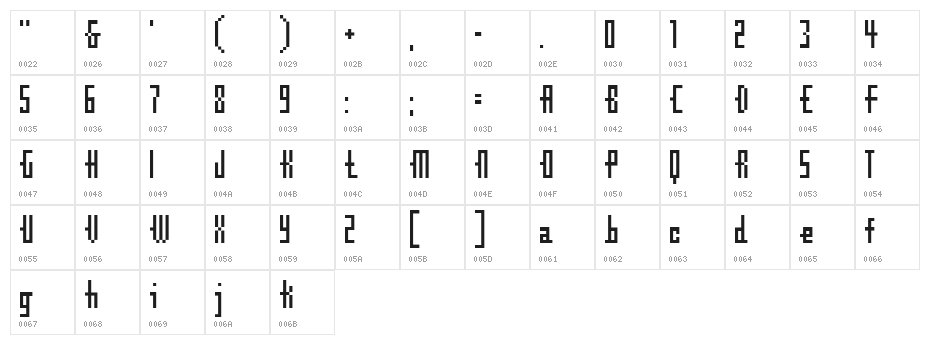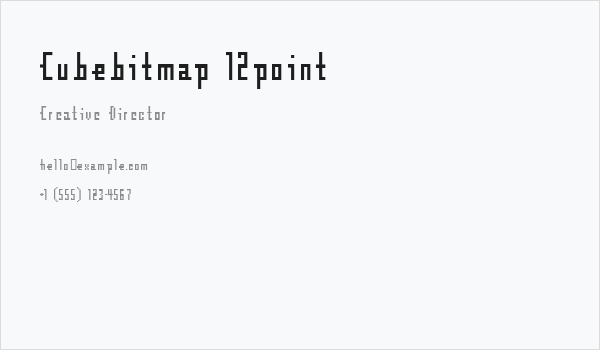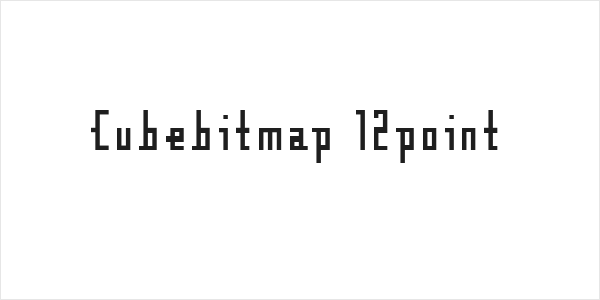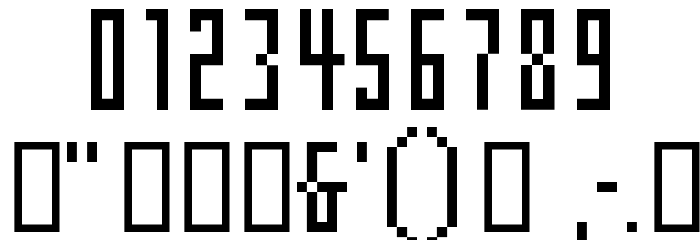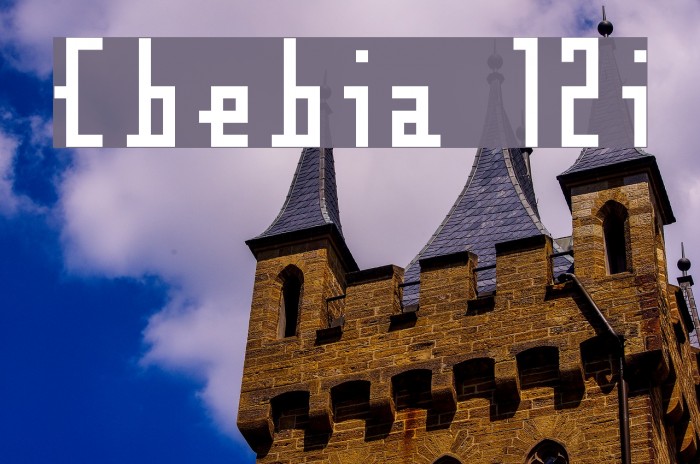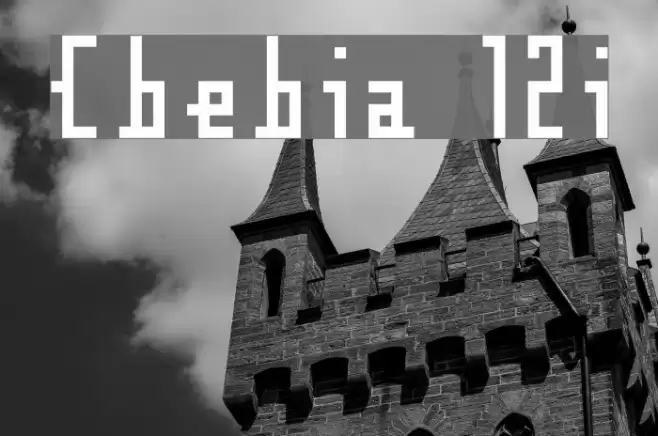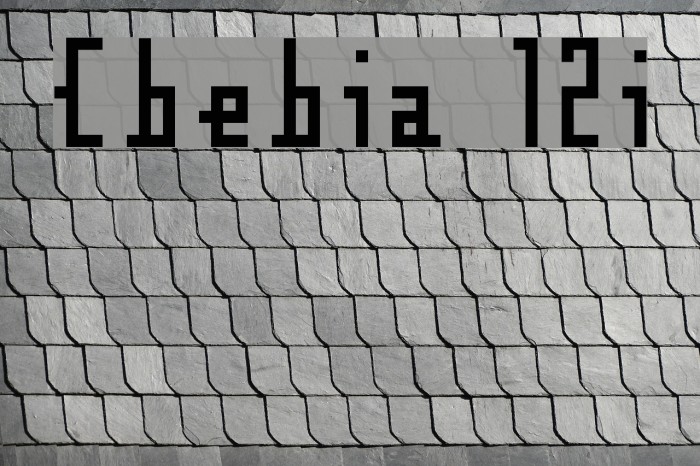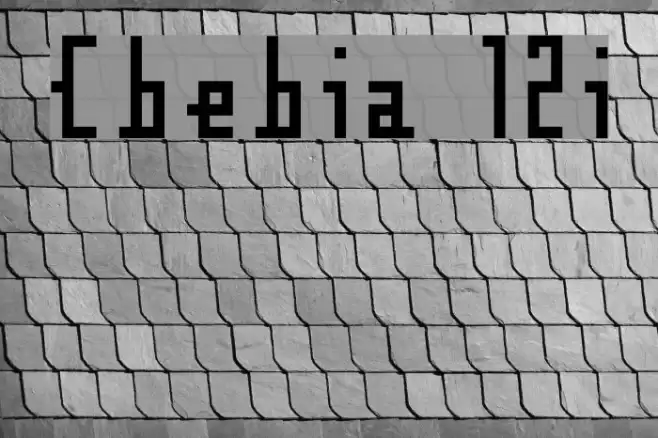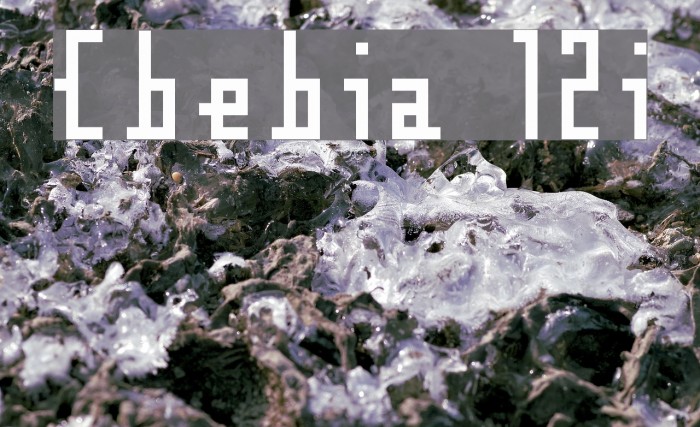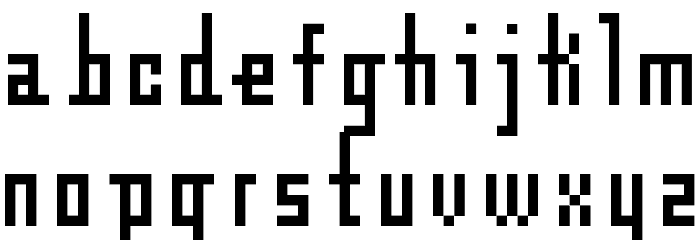
Cubebitmap 12point Font
✎ Pixel
| Gesamtstil | Retro, Digital |
| Anwendungsfall | Headlines, Logos, Digital Interfaces |
| Vorgeschlagene Projekte | Ideal for retro video games, digital interfaces, pixel art projects, and any design requiring a vintage digital aesthetic. |